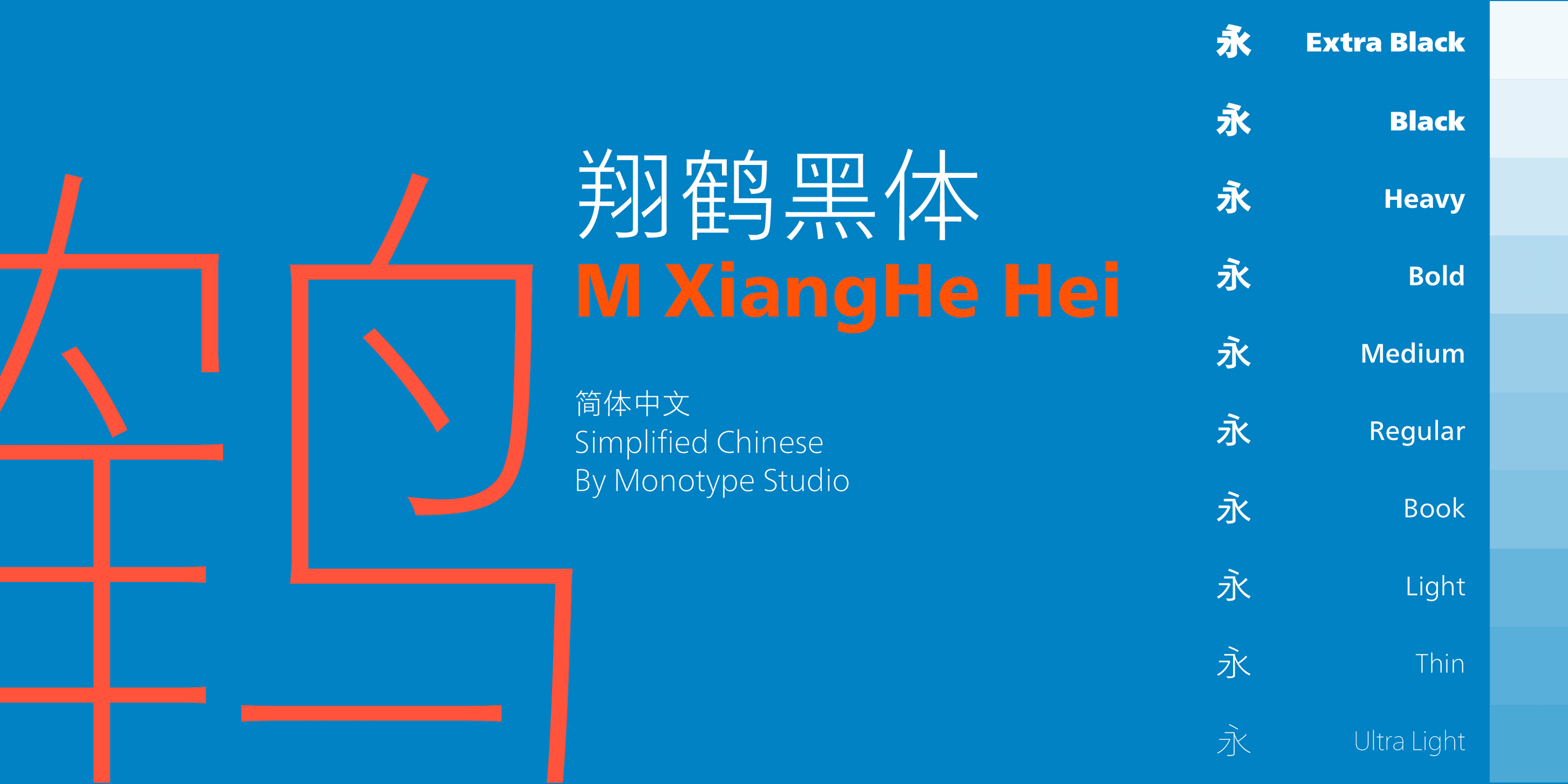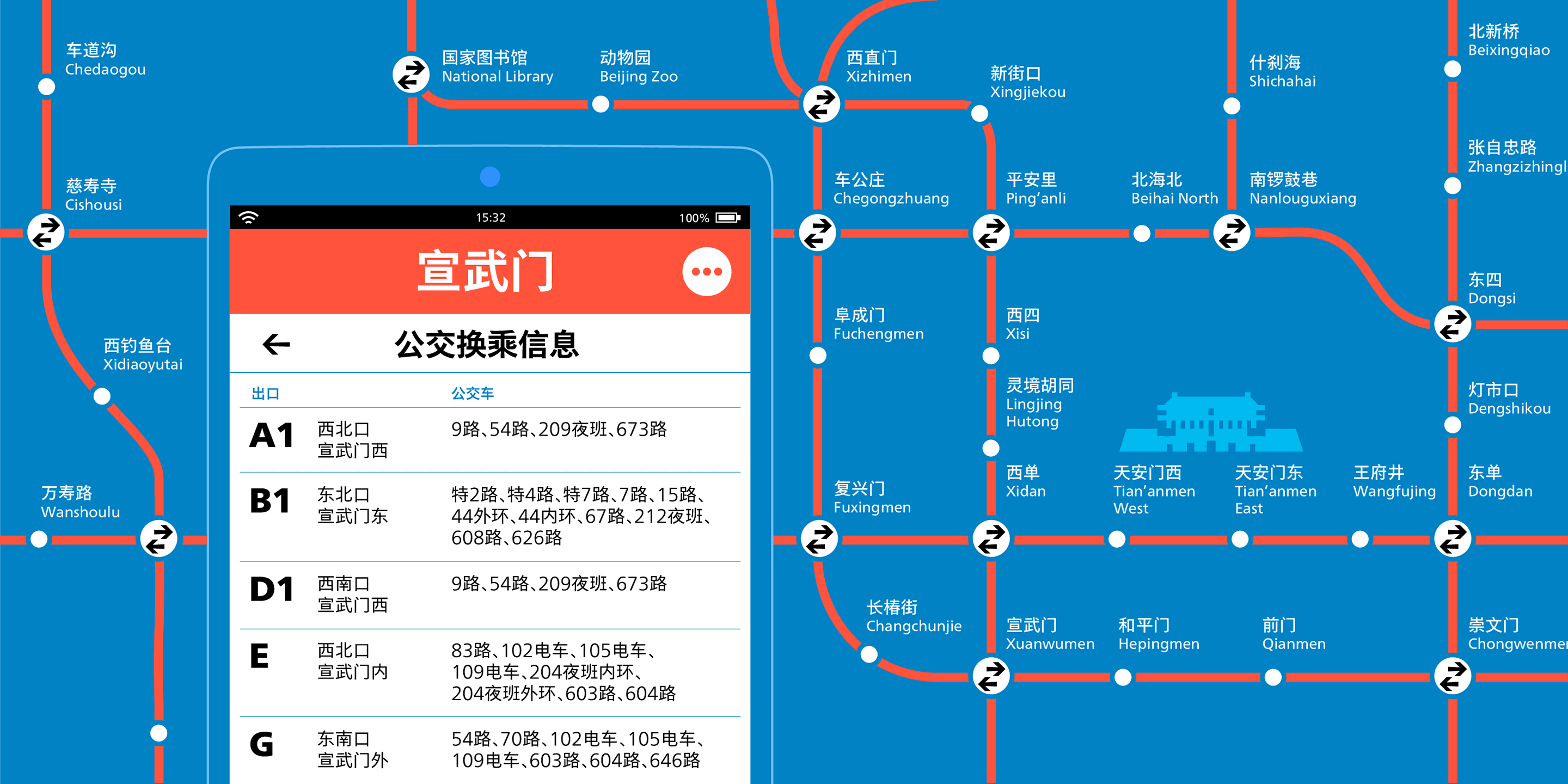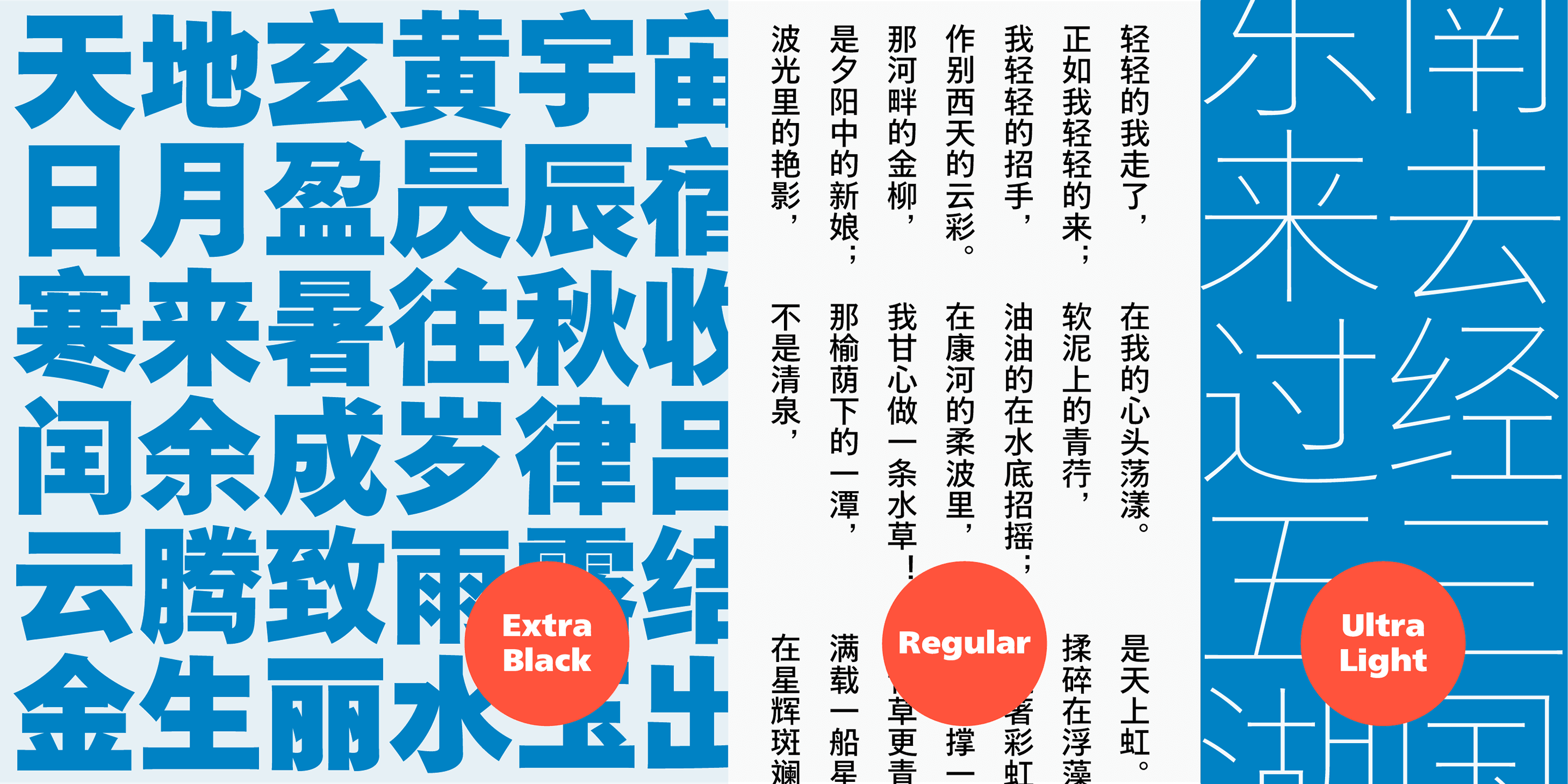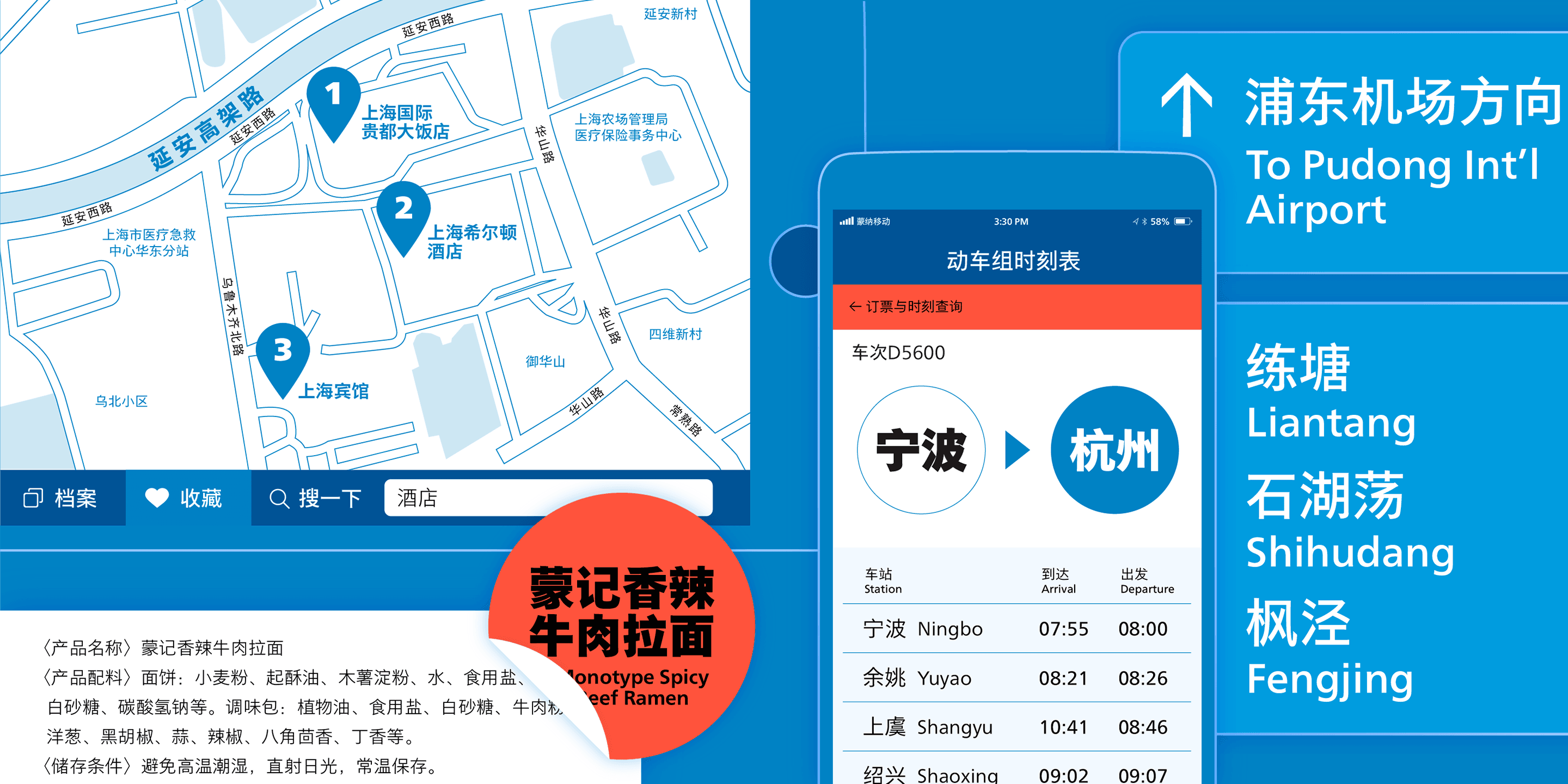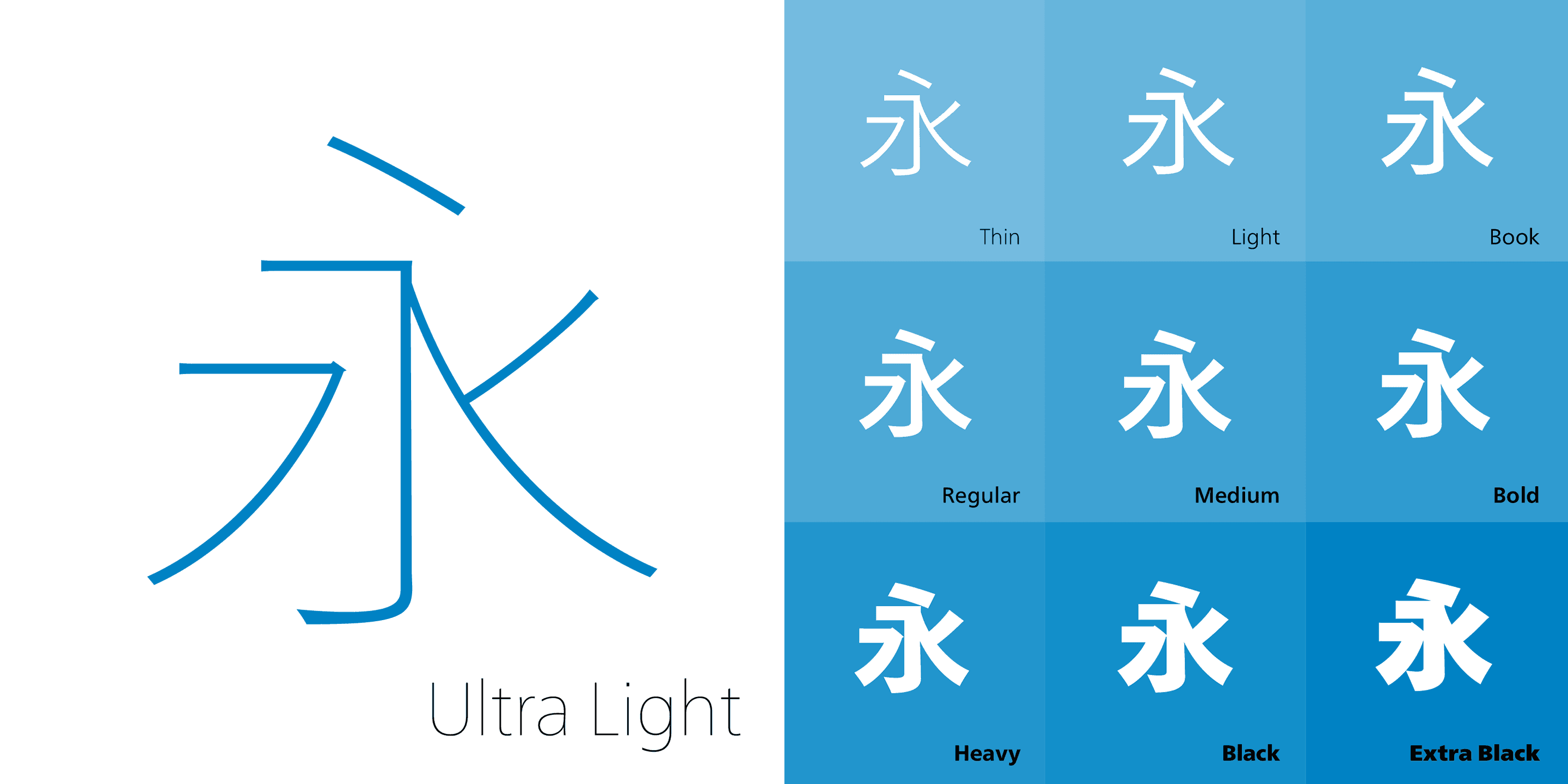
M XiangHe Hei
두루미처럼 우아한 서체
모노타입의 M XiangHe Hei체는 Neue Frutiger 기반으로, 두루미의 우아함과 해서의 미학을 담은 중국어 흑체입니다. 작은 글자폭과 부드러운 곡선, 10가지 웨이트로 다양한 디지털·인쇄 환경에서 뛰어난 가독성과 브랜드 일관성을 제공합니다.